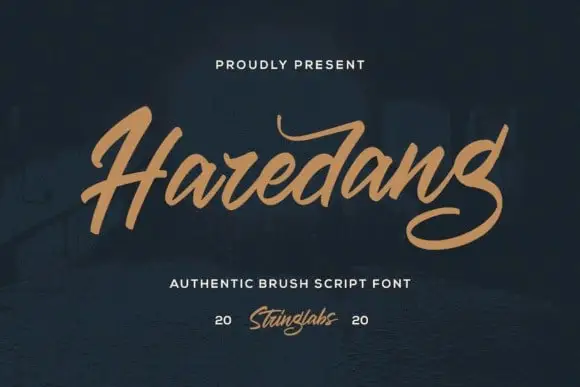
Haredang Script Font
Introduzimos a Haredang Script Font, uma tipografia chamada Calligraphy com estilo casual-chic que se enriquece com uma magia na pressão do dedo. Esta fonte foi projetada e compartilhada pela StringLabs. É uma fonte escrita à mão, com toques elegantes, perfeita para seus próximos projetos. Caçamos seu estilo distintivo e eterno, te encantando com sua beleza incrível e o ajudando a criar designs mágicos. Esta font é ideal para logotipos, letras de pasta, cartazes, design de roupas, etiquetas e muito mais. Adore seu toque elegante na Haredang Script Font e use-a como desejar. Seja para fazer logomarcas, letras personalizadas ou até mesmo etiquetas em sua próxima impressão, ela certamente dará um toque especial e único a seus projetos.